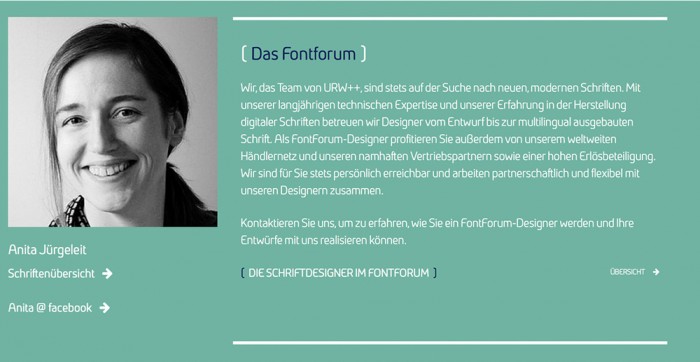
URW++ kommt mit neuer Homepage daher
Was mir nach 2 Minuten rumklicken auffiel:
Die »Ihr Text« Vorschau erlaubt nur 2stellige Punktgrößen und die Vorschau enthält immer die komplette A-z a-z Vorschau + meinem Wunschtext unten dran?
Sonderzeichen werden als Entity Name gerendert?
Mir ist völlig unklar welche Schriften als web font Lizenz verfügbar sind. Selbst die erweiterte Suche kennt keinen Filter nach Lizenzart.
Weitergucken machte dann schon kein Spaß mehr. Generell kommt die Seite auch sehr überladen daher, die Navigation hat so manche Uni schon besser gelöst finde ich.
Sonderzeichen werden als Entity Name gerendert?
Immerhin wohl nur die Handvoll von Zeichen, die in HTML besondere Bedeutung haben, also &<>"'. Mit allen anderen Unicode-Zeichen (incl. „“»«Őẞ usw. usf.) scheint es zu funktionieren – so der Font sie denn mitbringt.
Insgesamt teile ich dein Urteil wahrscheinlich: die Seite erscheint weder besonders schick und modern noch intuitiv oder besonders anwenderfreundlich.
Hm, mal von den sehr sympathisch aussehenden Mitarbeitern abgesehen, die die Seite schmücken und nett machen, ist mir der Fließtext viel zu eng gesetzt, das ist unbequem! Im Versalsatz ist die Schrift dann noch schwerer zu lesen. Absicht oder Darstellungswidrigkeit? :-?
Ging mir genauso. Blöde Schrift in Weiß auf Helltürkis, gequetschte Versalzeilen, genauso lesefeindlich wie eine Shampooflasche – und auch in der Farbe eines Waschmittels. Aber überflüssige Klammern: »Wir wollten einen Akzent setzen«. Dieses Barrierendesign sehe ich in letzter Zeit ständig im Museum. Manchmal zottle ich dann die Lesebrille raus, obwohl die Schrift groß ist. Aber dann kann ich es immer noch nicht lesen, ohne daß es flimmert, und nach dem dritten Schild habe ich genug. Angebracht auf einer Höhe, zu der sich kleine alte Damen bücken müssen. Das Wirken von Designern, die originell, kreativ, individuell und überhaupt anders sein wollen und darüber ihren Job nicht erledigen. Und offenbar jeden verständigen Museumsmitarbeiter zum Schweigen bringen können. Eine Pest.
nicht nur das die schrift zu klein und unpassend für den mengentext ist, das menü mit den niedrigaufgelösten bildern (die auch nicht gerade zum klicken einladen) ist einfach zuviel text, stichpunkte hätten es auch getan. wie martin schon schrub, das durchziehen mit der klammer in den headlines und in der navi ist ein netter gag aber total überflüssig.
dazu kommen noch die unvorteilhaften banner. urw schafft es leider immer wieder ihre eigene schriften dermaßen schlecht aussehen zu lassen, dass man diese gar nicht mehr ausprobieren will. das ist mir im newsletter auch schon aufgefallen.
selbst der webfont wird bescheiden gerendert.
auch die beispielbilder der schriften und vorschaubilder sind als gif hinterlegt und werden in der ansicht hochskaliert, dabei werden diese ziemlich weichgezeichnet, verstehe ich nicht wieso man sowas dem kunden anbietet. :neenee:
wenn ich bei einer schrift auf die links kurzinfo, designer, klassifikation etc. klicke passiert irgendwas auf der rechten seite, ich sehe aber irgendwie nix. anscheinend fehlen die inhalte noch.
Aaaber … das ist doch sogar responsive. Also ich meine mich an die Nachricht zu erinnnern, zwei Flensburger Webdesigner wären für den Relaunch, der nun nach zehn Jahren oder so ähnlich – immerhin! – erfolgt ist, verantwortlich. Ob das nun die Hausdesigner sind, die schon seit Jahren auch die gifs für die neuen Schriften erstellen – gut möglich. Auch die Text-Vorschau gab es in ähnlicher Form im alten Auftritt. Vielleicht wird der nicht sooo lesbare webfont (Ribera) ja auch gelegentlich mal gewechselt. Immerhin jetzt mal ein Relaunch.
Im (Re)Design scheint die – gut gemeinte und leider etwas verkopfte – Idee verfolgt worden zu sein, URW++ analog zu Fontshop oder Linotype eine, sagen wir mal, letztgültige duale Farbigkeit zu geben, abgeleitet von der Farbigkeit des Logos – türkis und dunkelblau – gleich noch typografisch ergänzt durch die aus dem Logo abgeleiteten Klammern. Im Ergebnis vielleicht etwas zu exzessiv eingesetzt. Wegen »urw schafft es immer wieder usw.« – ja, so isses. Man kann sich URW-Schriften aber auch auf anderen Plattformen anschauen (s. meine Signatur), MyFonts, sogar FontShop …
hochzwei hat die seite gestaltet.
das sie seite responsive ist, ist natürlich toll auch wenn man hier noch etwas nacharbeiten könnte. der webfont funktioniert aber hier schon besser als am bildschirm. trotzdem ist mir das too much.
bei klick auf die logos unter identitype bekomme ich eine fehlermeldung. ups, jetzt ist gerade die komplette seite nicht mehr per smartphone erreichbar, da wird wohl noch gebastelt.
die farbmischung finde ich persönlich nicht ganz so schlimm.
das sie seite responsive ist, ist natürlich toll auch wenn man hier noch etwas nacharbeiten könnte.
Naja, sagen wir mal so: Wer in der zweiten Hälfte des Jahres 2015 eine Seite in diesem Umfang online stellt und diese nicht responsive umsetzt, der muss aber auch eine wirklich gute Entschuldigung dafür haben. Gibt's überhaupt noch Wordpress bzw. in diesem Falle TYPO3, Themes/Templates die aktuell und nicht responsive sind (ich meine die mit Verkaufszahlen > 0).
Man sagte mir übrigens just heute, das es angeblich nur ein Zwischenstand ist, der in den nächsten Wochen/Monaten noch verbessert werden soll.